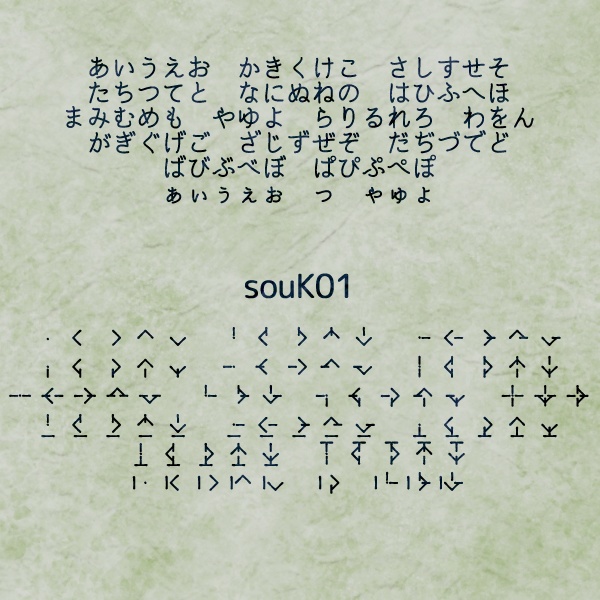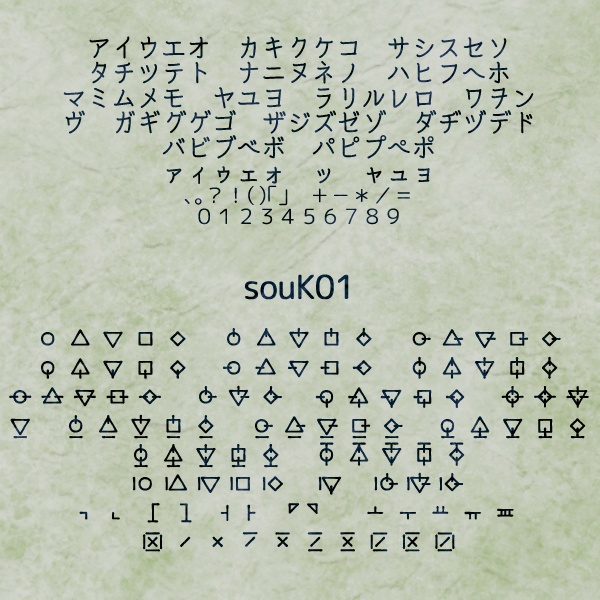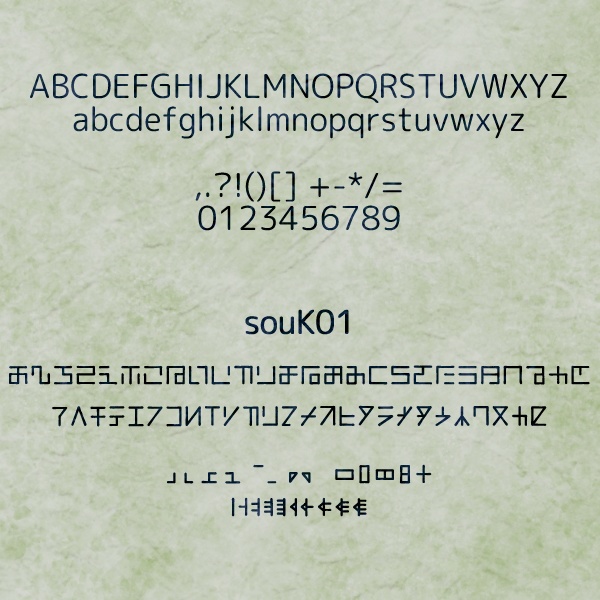
異国語・呪文フォント「souK01」
仮名・アルファベット入力による、未知の言語っぽい文字列を 作成するためのフォント(OpenTypeフォント)です。 仮名(全角)は等幅、アルファベット(半角)はプロポーショナルです。 【注意事項】 著作権は放棄しておりません。 意匠・商標登録などに使用することはご遠慮ください。 フォントデータの販売・再配布もご遠慮ください。 その他の使用についてはご自由に。 また、当フォントの使用により損害などが生じても、 一切の責任を負いませんのでご了承ください。 【タイプ可能な文字】 あいうえお かきくけこ さしすせそ たちつてと なにぬねの はひふへほ まみむめも やゆよ らりるれろ わをん がぎぐげご ざじずぜぞ だぢづでど ばびぶべぼ ぱぴぷぺぽ ぁぃぅぇぉ っ ゃゅょ アイウエオ カキクケコ サシスセソ タチツテト ナニヌネノ ハヒフヘホ マミムメモ ヤユヨ ラリルレロ ワヲン ヴ ガギグゲゴ ザジズゼゾ ダヂヅデド バビブベボ パピプペポ ァィゥェォ ッ ャュョ 、。?!()「」+-*/= 0123456789 ABCDEFGHIJKLMNOPQRSTUVWXYZ abcdefghijklmnopqrstuvwxyz ,.?!()[]+-*/= 0123456789